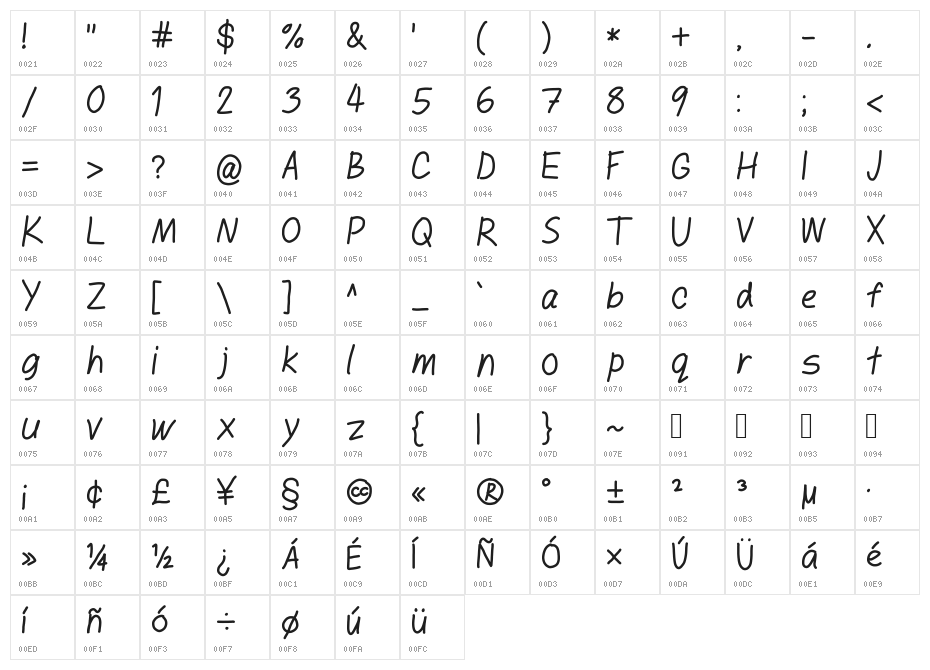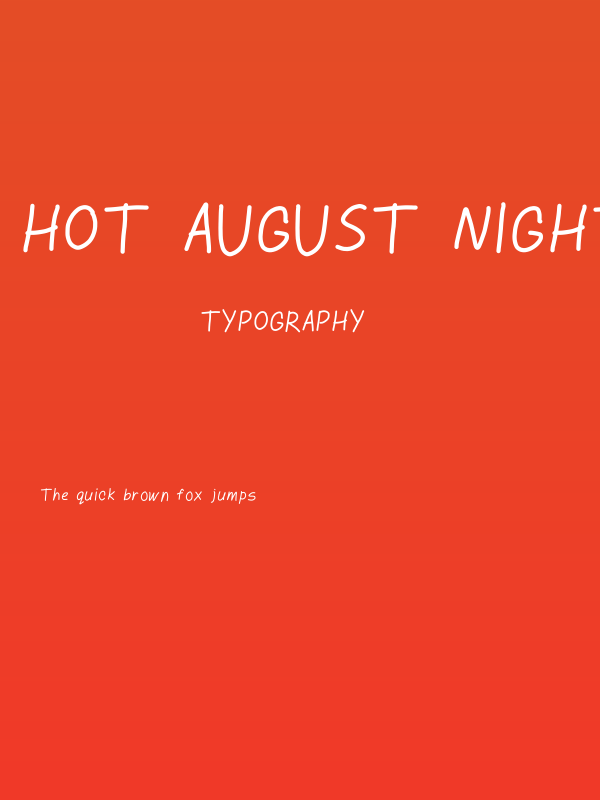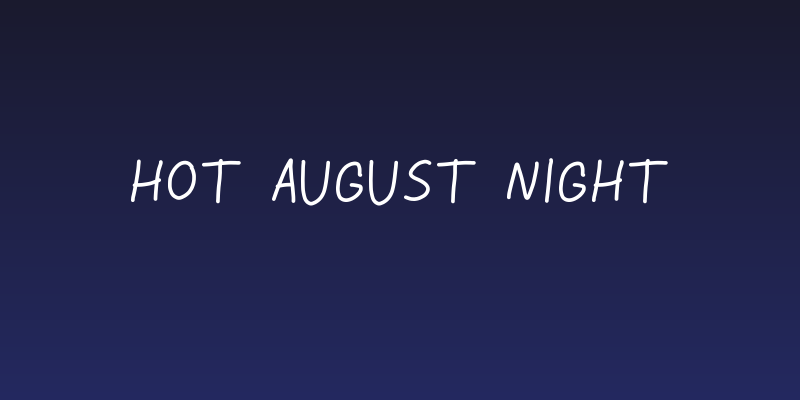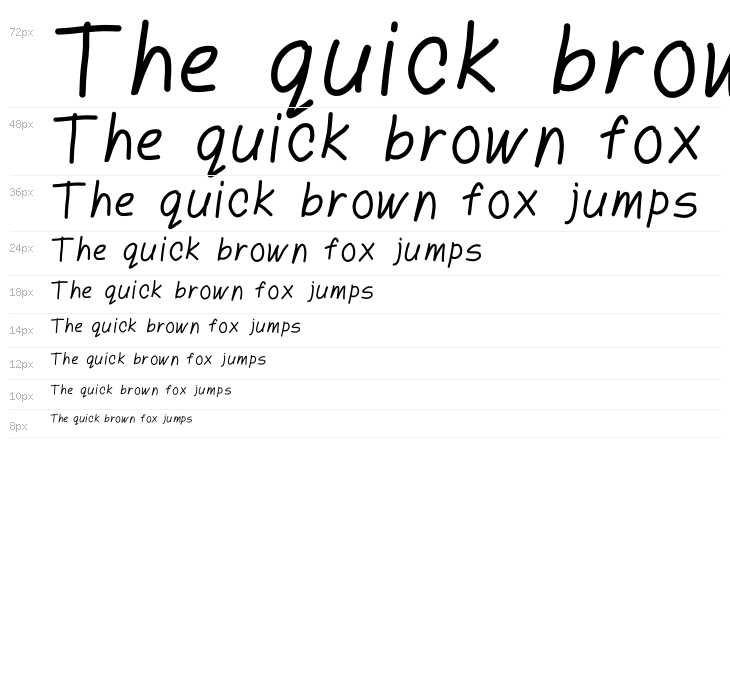
Hot August Night Font
| Stile generale | Casual |
| Caso d'uso | Headlines, Informal text, Personal projects |
| Progetti proposti | Ideal for greeting cards, personal blogs, informal invitations, and children's books. |